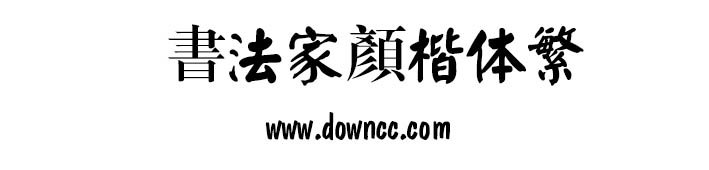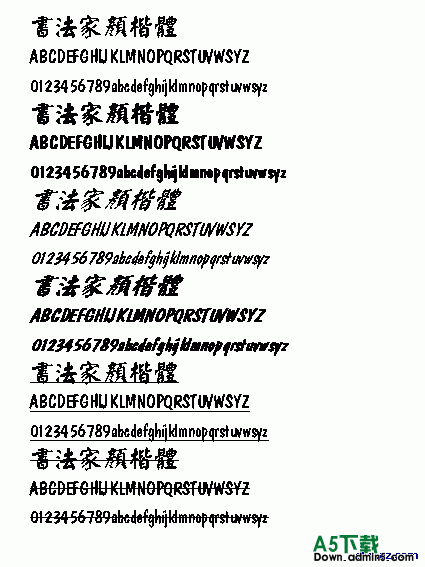
書法家顏楷體繁是很多練習(xí)書法的朋友比較喜歡的一種字體,它的每一筆、一頓都給人以力量感,看到讓人心曠神怡,需要的用戶快到綠色資源網(wǎng)下載體驗(yàn)吧!
這款書法家顏楷體字體字形牽絲勁挺,同樣濃同樣纖,適用于繪畫設(shè)計(jì)、藝術(shù)創(chuàng)作等領(lǐng)域。本文為整理了對(duì)于字體的安裝方法。